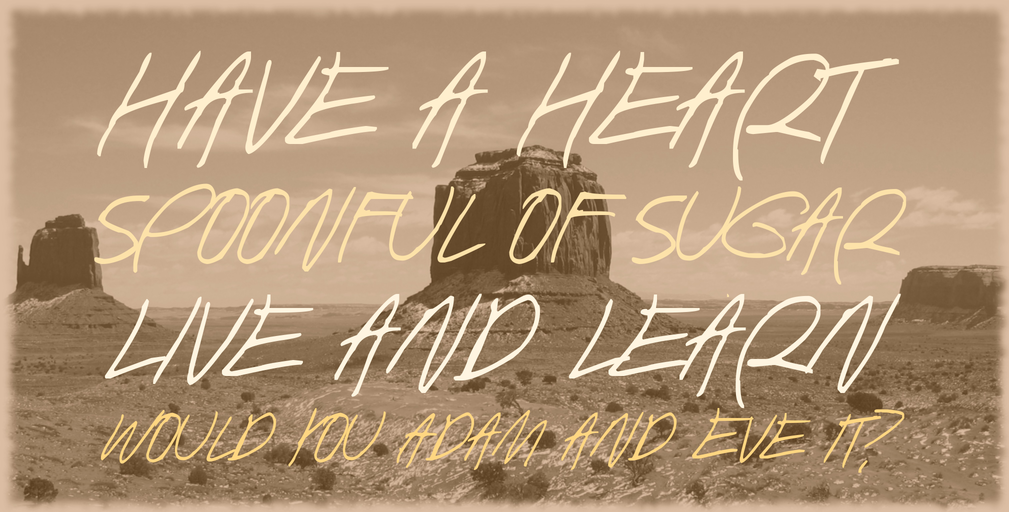
Estamos entusiasmados por você descobrir a ‘Human Being Font’, uma fonte script que transmite naturalidade e humanidade. Ideal para trabalhos pessoais, esta elegante fonte expressa sentimentos profundos através de linhas suaves e formas delicadas. A Hamilton desenvolveu essa hermosa fonte, inspirada em conversas fluidas e em movimentos naturais dos lábios. Quer usar ela em um projeto comercial? Basta nos contatar para adquirir uma licença comercial. Você pode entrar em contato conosco através de nosso link PayPal ou até mesmo do botão ‘Doar’ próximo ao botão de download. Ainda não está pronto para pagar? Não se preocupe, nossa equipe aprecia contribuições regulares. Esta fonte é perfeita para criações que expressam empatia e conectividade humana, seja em aplicativos móveis, livros digitais ou impressos. Sempre buscamos oferecer a melhor experiência ao criar uma fonte de alta qualidade e versátil. Aqui está nossa ‘Human Being Font’, uma fonte script perfeita para quem valoriza a simplicidade e a profundidade na comunicação visual.